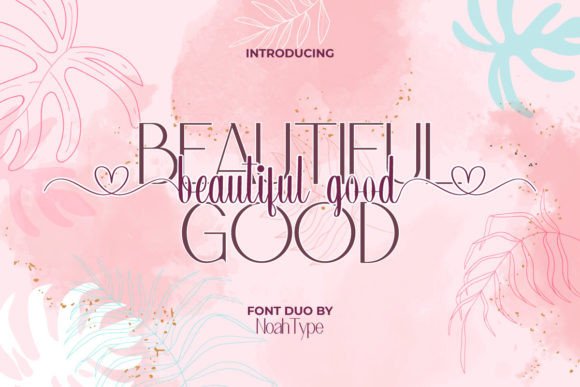
Beautiful Good Duo
Việc tìm kiếm các thành phần thiết kế phù hợp có thể là một thách thức, nhưng Beautiful Good Duo cung cấp một bộ sưu tập đặc biệt giúp nâng tầm công việc của bạn ngay lập tức.
Cho dù bạn đang tạo sản phẩm POD (In theo yêu cầu), thiệp mời đám cưới hay đồ họa mạng xã hội, Beautiful Good Duo đều là một sự lựa chọn lý tưởng.